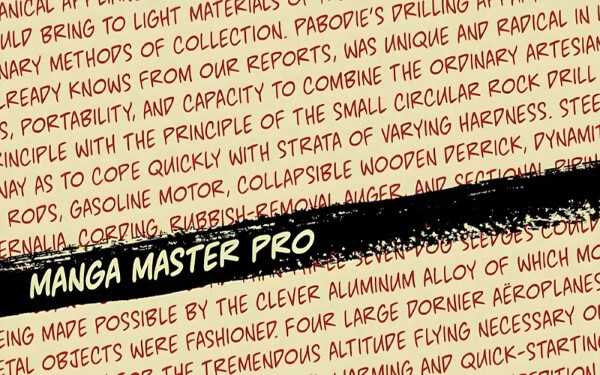
Font chữ truyện tranh không chỉ đơn thuần là một công cụ thể hiện văn bản, mà còn là cầu nối cảm xúc giữa người sáng tạo và độc giả. Một bộ phông chữ miễn phí truyện tranh phù hợp sẽ khiến từng lời thoại, từng biểu cảm nhân vật trở nên sống động và gần gũi hơn. Ngược lại, nếu font chữ khô cứng hoặc thiếu sức hút, độc giả sẽ khó cảm nhận được trọn vẹn tinh thần của câu chuyện.
Do được sử dụng trong nhiều thể loại truyện khác nhau — từ hành động, lãng mạn cho đến hài hước — nên mỗi font chữ truyện tranh lại mang một phong cách riêng. Việc lựa chọn phù hợp còn phụ thuộc vào gu thẩm mỹ, ý đồ sáng tạo và cảm xúc mà tác giả muốn truyền tải. Dưới đây là tổng hợp 8+ phông chữ truyện tranh miễn phí đã được Việt hoá đẹp nhất, được nhiều nhóm edit, nhà thiết kế và tác giả sử dụng rộng rãi trong thời gian qua.
1. Font Teddy Bear
Bộ phông chữ miễn phí truyện tranh Teddy Bear do nhóm dịch Wonderland phát triển, ban đầu chỉ dành riêng cho việc edit manga. Tuy nhiên, nhờ sự yêu thích từ cộng đồng, font này đã được Việt hoá hoàn chỉnh và chia sẻ công khai.
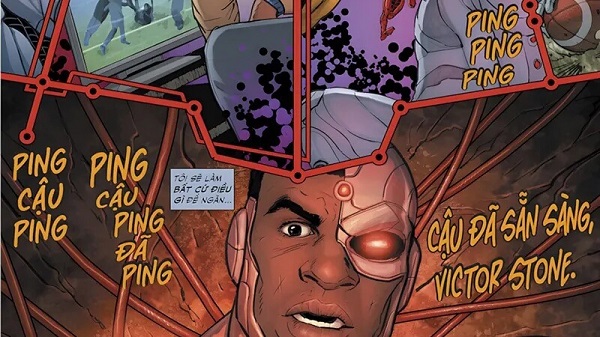
Teddy Bear mang phong cách tròn trịa, dễ thương, phù hợp cho những câu chuyện tình cảm, học đường hoặc thể loại slice of life. Bộ font có hơn 100 kiểu chữ, hỗ trợ Unicode đầy đủ, giúp bạn dễ dàng nhập tiếng Việt mà không bị lỗi dấu. Đây là lựa chọn tuyệt vời cho ai đang tìm font chữ truyện tranh miễn phí vừa đẹp vừa dễ dùng.
2. Font Anime Ace 3 Việt hoá
Nếu bạn là người yêu thích truyện Nhật, chắc hẳn đã từng thấy qua phông chữ truyện tranh miễn phí Anime Ace 3. Bộ font này xuất hiện trong hàng loạt manga đình đám, mang nét chữ mạnh mẽ, rõ ràng và dễ đọc.
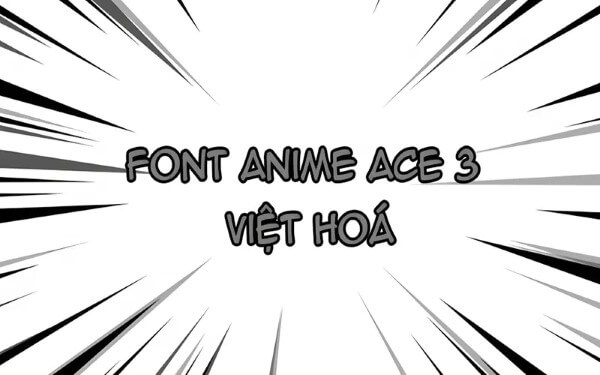
Phiên bản Việt hoá của Anime Ace 3 giúp người dùng sử dụng thuận tiện hơn, giữ nguyên form chữ đậm chất comic. Đây là lựa chọn hàng đầu cho các nhóm edit chuyên nghiệp, vì nó phù hợp với mọi thể loại truyện, từ hành động cho đến phiêu lưu.
3. Font HL Comic
HL Comic là sản phẩm của nhà thiết kế Hùng Lân – người từng nổi tiếng với nhiều bộ font như VNI-OngDoHL hay HLThuphap. Bộ font chữ truyện tranh việt hóa này sử dụng bảng mã Unicode, giúp hiển thị mượt mà và dễ chỉnh kích cỡ chữ.
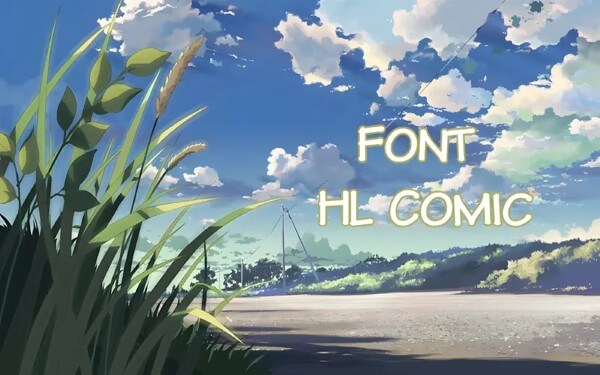
HL Comic có đặc điểm là nét chữ mềm mại nhưng không mất đi sự tinh tế, phù hợp với các truyện mang phong cách nhẹ nhàng hoặc những trang webtoon Việt Nam. Font này giúp người dùng tối ưu trong việc trình bày thoại và hiệu ứng trong khung truyện.
4. Font MTO
MTO là một trong những phông chữ miễn phí truyện tranh được người dùng Việt yêu thích nhất hiện nay. Font được phát triển bởi nhóm MTO với nhiều phiên bản khác nhau về độ đậm, độ nghiêng và kích thước.
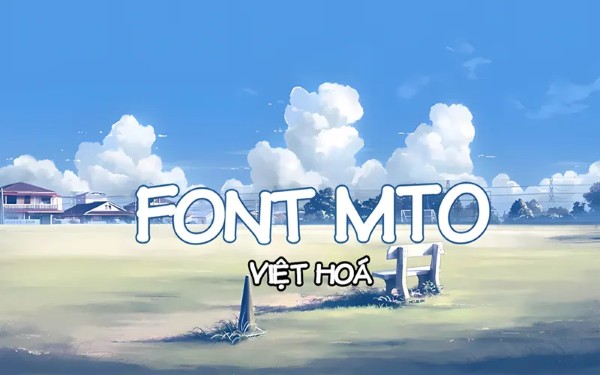
Điểm mạnh của MTO là khả năng biến hóa linh hoạt — có thể sử dụng trong các truyện hài hước, phiêu lưu hoặc hành động đều phù hợp. Các ký tự được thiết kế rõ nét, khoảng cách giữa các chữ vừa đủ để tạo cảm giác dễ chịu cho người đọc.
5. Spider Man Font
Như tên gọi, Spider Man Font lấy cảm hứng từ loạt truyện siêu anh hùng nổi tiếng. Với những đường nét góc cạnh, kiểu chữ này thể hiện năng lượng, sức mạnh và sự kịch tính của từng khung truyện.
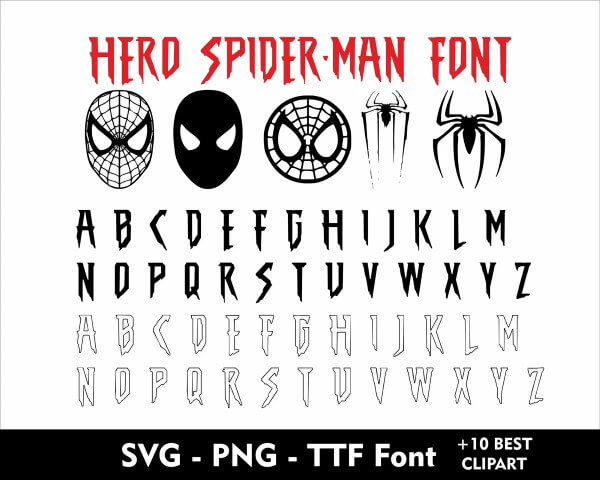
Đây là font chữ truyện tranh miễn phí lý tưởng cho những ai sáng tác truyện hành động hoặc siêu anh hùng. Khi được Việt hoá, Spider Man Font vẫn giữ được cá tính mạnh mẽ vốn có, đồng thời hiển thị tiếng Việt cực kỳ ổn định.
6. Font MTO Astro City
Cũng thuộc “hệ sinh thái” MTO, bộ phông chữ miễn phí truyện tranh MTO Astro City mang phong cách hiện đại và có phần “vũ trụ” hơn. Font này thường được dùng trong các tác phẩm sci-fi, fantasy hoặc siêu nhiên.
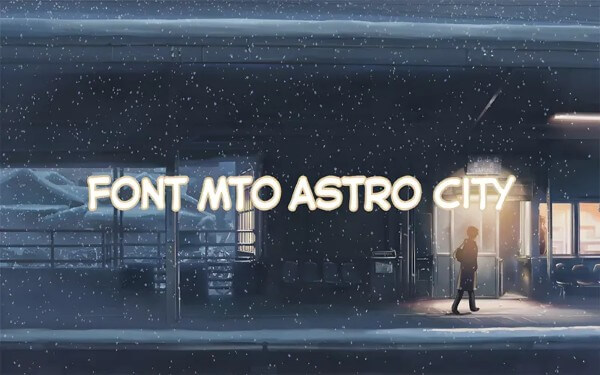
Các đường nét uốn cong và khoảng cách cân đối giúp tạo cảm giác công nghệ cao. Với khả năng hiển thị tiếng Việt mượt mà, MTO Astro City là lựa chọn hấp dẫn cho cả designer và nhóm dịch muốn mang lại sự mới mẻ cho trang truyện của mình.
7. Font LNTH
Font LNTH là đại diện tiêu biểu cho sự tinh tế trong thiết kế Việt. Dù không quá cầu kỳ, nhưng từng nét chữ đều được trau chuốt, giúp thể hiện tốt lời thoại, cảm xúc nhân vật và âm thanh trong truyện.
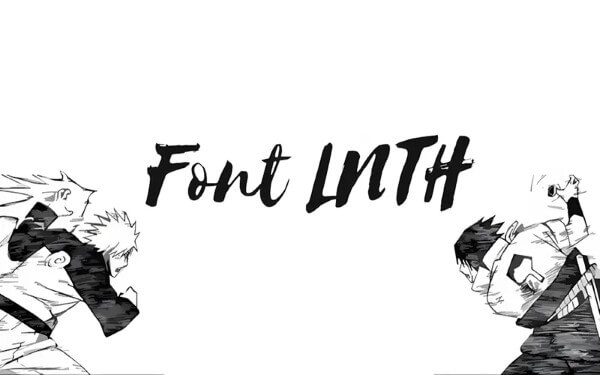
Bộ phông chữ truyện tranh miễn phí này có nhiều biến thể khác nhau, hỗ trợ đầy đủ tiếng Việt, phù hợp với cả tác phẩm cổ điển lẫn hiện đại. LNTH cũng là font được các nhóm edit chuyên nghiệp sử dụng rộng rãi nhờ tính dễ đọc và nhẹ file.
8. Font UEE
UEE là một trong những font mang đậm phong cách manga Nhật Bản. Với đường nét mềm, cao và thanh thoát, font này thường được dùng trong những đoạn thoại cảm xúc hoặc độc thoại nội tâm.
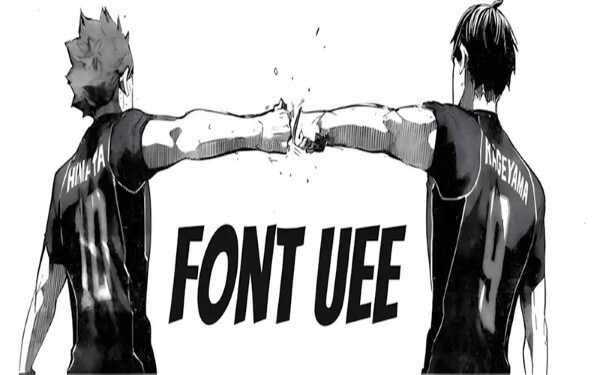
Khi Việt hoá, UEE vẫn giữ được toàn bộ sự tinh tế của bản gốc, đồng thời đảm bảo khả năng hiển thị tiếng Việt rõ ràng. Nếu bạn đang tìm font chữ truyện tranh việt hóa có tính nghệ thuật cao, thì đây chính là lựa chọn không nên bỏ lỡ.
9. Font TiS
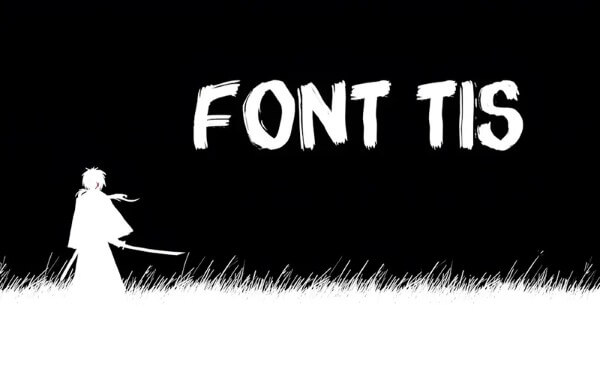
Font TiS nổi bật bởi sự hoàn chỉnh trong từng ký tự, hỗ trợ tốt các dấu tiếng Việt và ký hiệu đặc biệt. Các nhà thiết kế thường chọn TiS cho các truyện có nhịp nhanh hoặc thoại dày, vì độ cân bằng giữa chữ và khoảng trắng rất tốt. Đây là một trong những phông chữ miễn phí truyện tranh được yêu thích nhất nhờ tính ứng dụng cao, dễ kết hợp với nhiều phong cách thiết kế khác nhau.